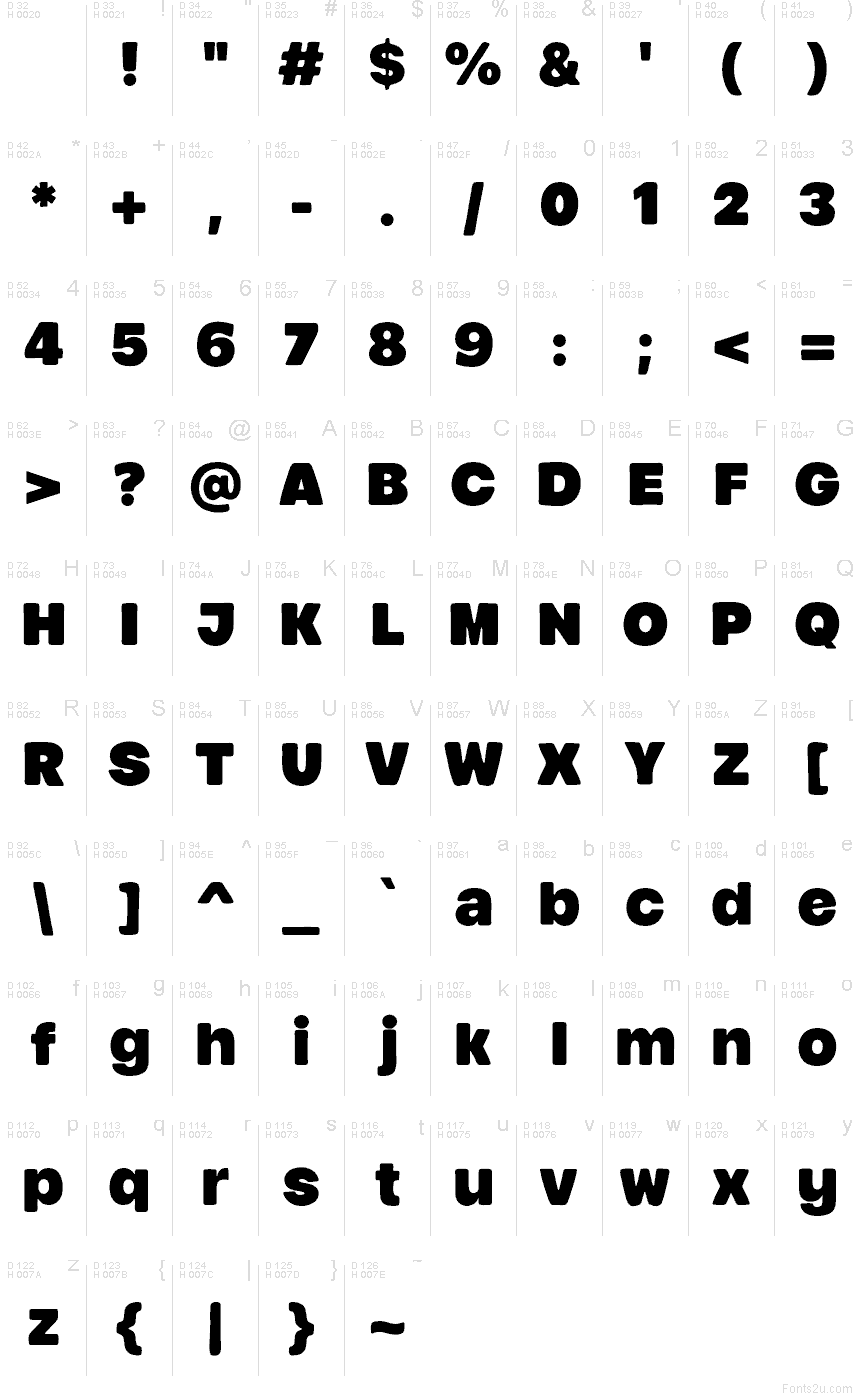
Friend Bestie par Namara Creative est une police d'affichage gratuite au style cartoon, caractérisée par des formes rebondies, douces et un esprit ludique qui rappelle les jouets. Ses tracés épais restent bien arrondis, tandis que les courbes légèrement irrégulières et les liaisons compactes donnent aux lettres un aspect décontracté, loin de la rigidité.
Elle est idéale pour les couvertures de livres pour enfants, les emballages de snacks, les invitations de fête et les visuels créatifs pour les réseaux sociaux. En tant que police gratuite, elle est particulièrement efficace là où quelques mots conviviaux suffisent à porter le design. Sa silhouette dense et bulleuse convient aussi parfaitement aux titres courts et aux cartouches de texte, où ces formes généreuses ont l'espace nécessaire pour faire passer un message simple et joyeux.